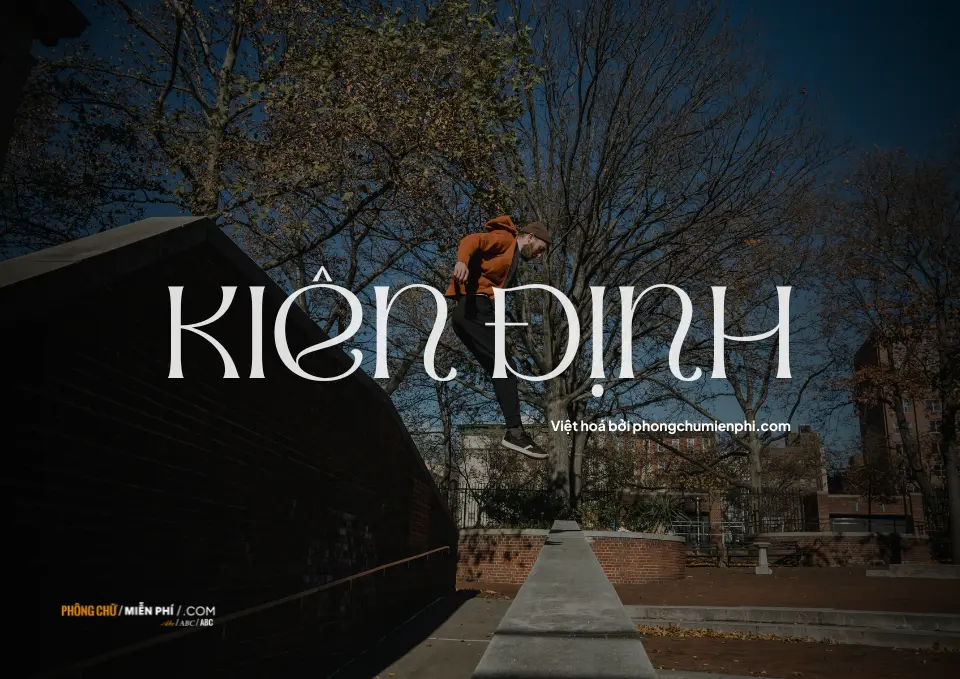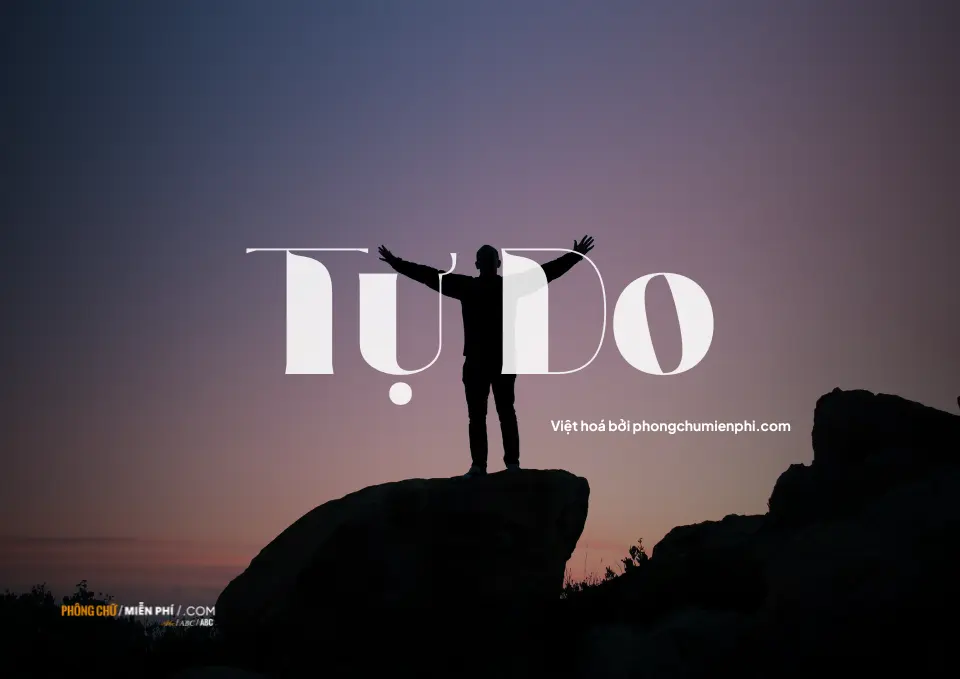
Font Việt hoá PCMP Vince
Font Việt hoá PCMP Vince do Sign Studio thiết kế là một phông chữ thời trang. Nó mang vẻ ngoài vừa hiện đại vừa hoài cổ – rõ ràng, hiện đại và vui nhộn. Mỗi cạnh của chữ đều được chế tác tỉ mỉ, mang đến chất lượng cao cấp. Phông chữ cổ điển
Đường cong có điểm nhấn sẽ được giữ nguyên hình học và mượt mà. Chữ ghép và chữ thay thế phong cách rất phù hợp để tạo ra nhiều biến thể thiết kế. Đa năng trong việc xây dựng thương hiệu, thiệp mời, logo, tiêu đề tạp chí và áp phích.
Vince phù hợp cho nhiều dự án khác nhau như thiệp mời văn phòng phẩm, mạng xã hội, logo, đám cưới, xây dựng thương hiệu, thiết kế đồ họa, bổ sung thêm một số bìa kẹp. Và có thể kết hợp với nhiều loại phông chữ serif khác nhau để hoàn thiện dự án bạn muốn thực hiện.